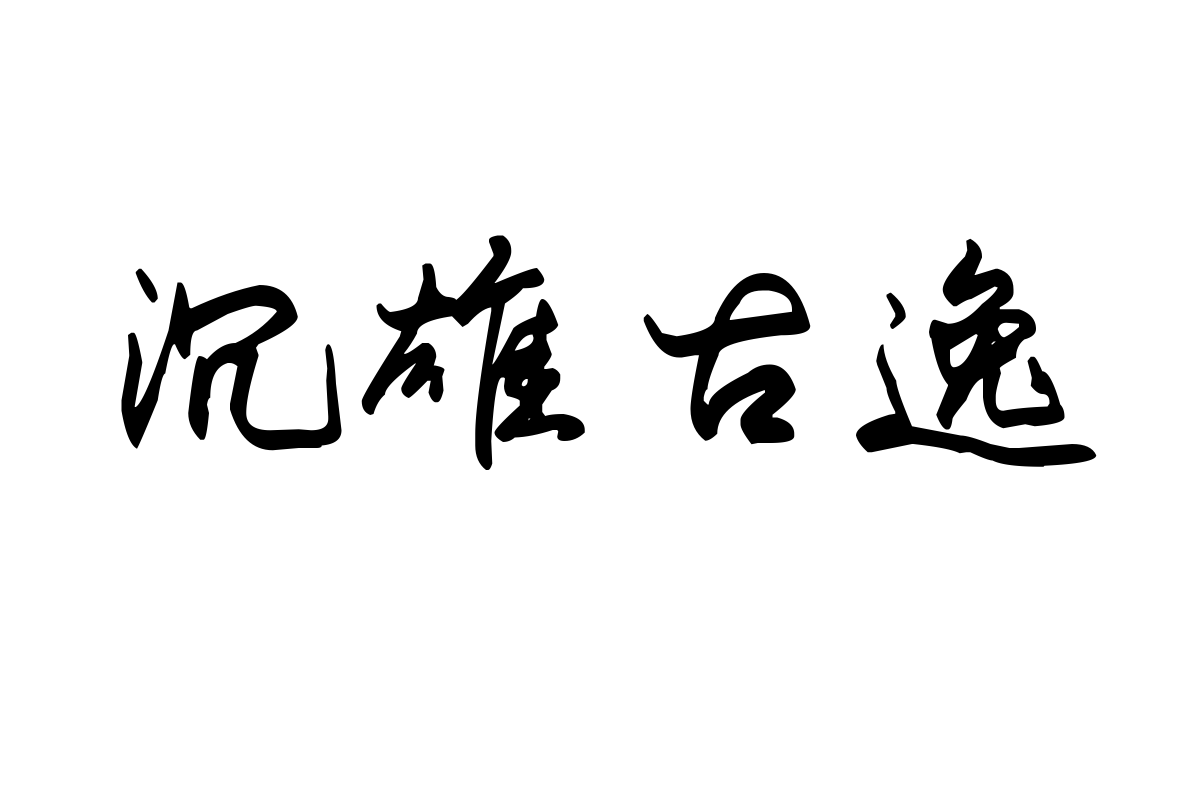
米开标准行书字体是一套由米开公司开发的中文字体,主要用于商业和正式场合的印刷品。该字体以其清晰的线条、优雅的字形和丰富的变化而受到广泛欢迎。
1. 笔画粗细:米开标准行书的笔画粗细适中,既不会过于粗犷,也不会过于细弱,使得文字看起来既清晰又美观。
2. 字形结构:该字体的字形结构规整,每个字的结构和位置都经过精心设计,使得整个字体看起来既统一又富有变化。
3. 风格特点:米开标准行书的风格庄重大方,适合用于各种正式场合的印刷品,如报纸、杂志、书籍等。同时,其简洁明了的特点也使得它在广告和标识设计中得到了广泛应用。
5. 可扩展性:米开标准行书字体不仅适用于商业和正式场合的印刷品,还可以应用于其他领域,如网页设计、图形设计等。用户可以根据自己的需求进行个性化定制,以满足不同的设计需求。
总之,米开标准行书字体以其清晰、优雅的字形和广泛的适用性,成为了一种非常受欢迎的中文字体。